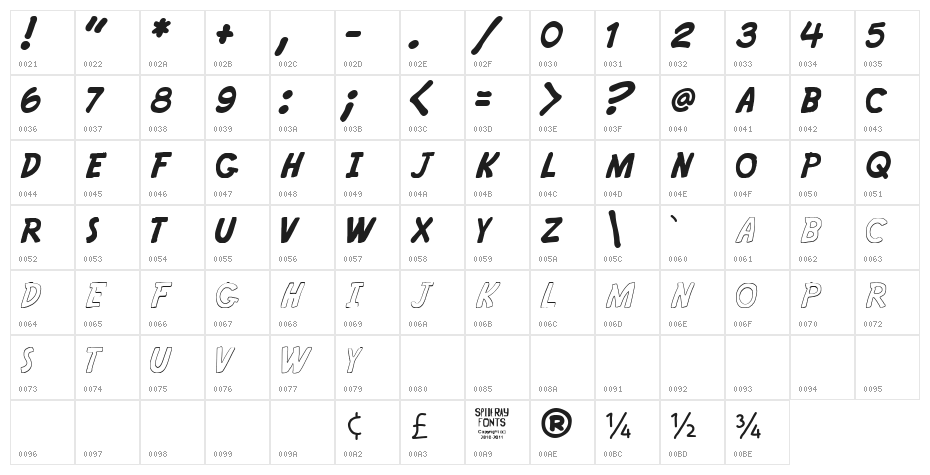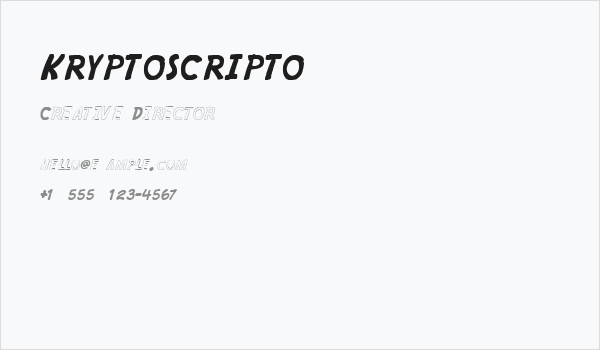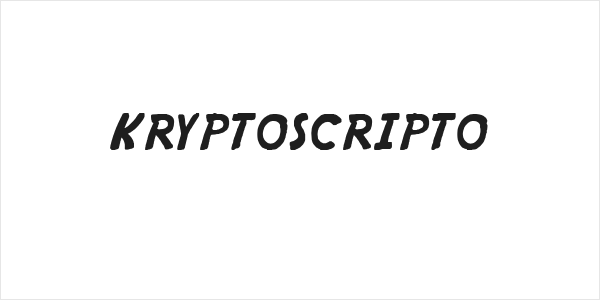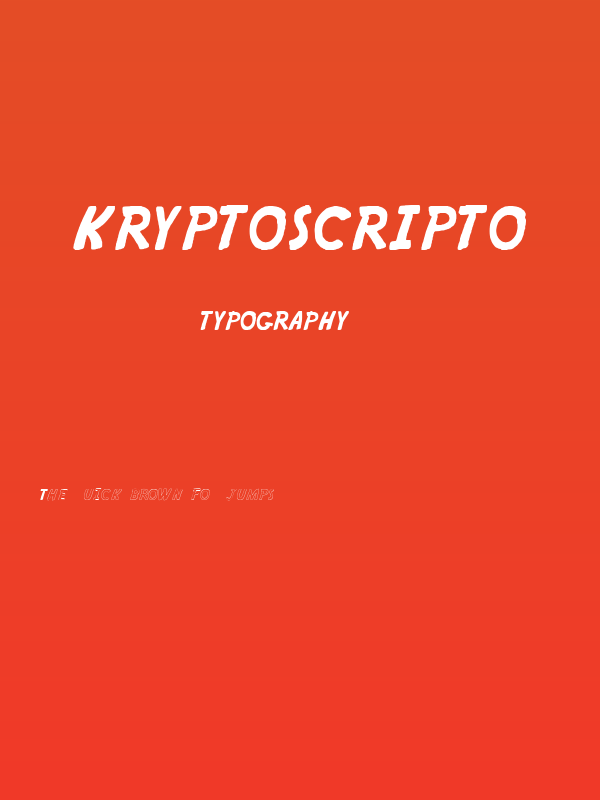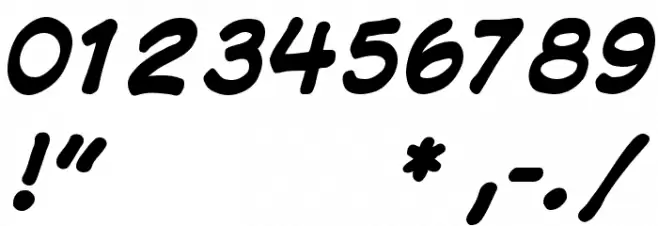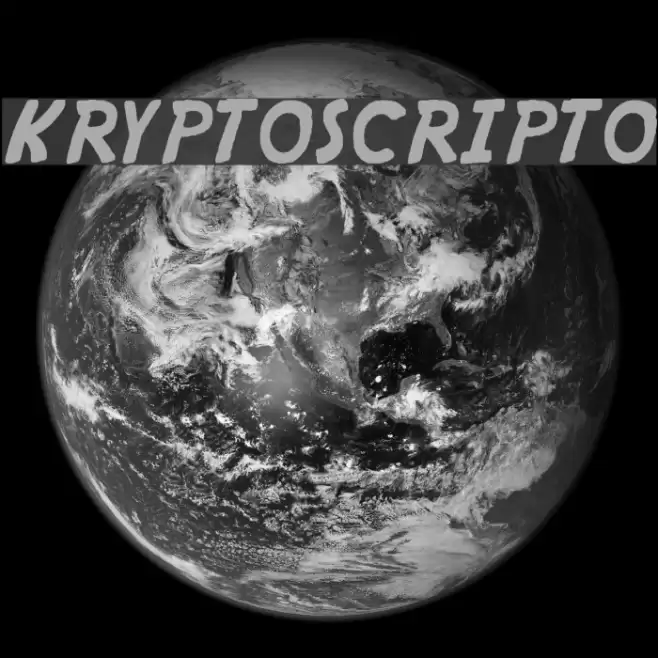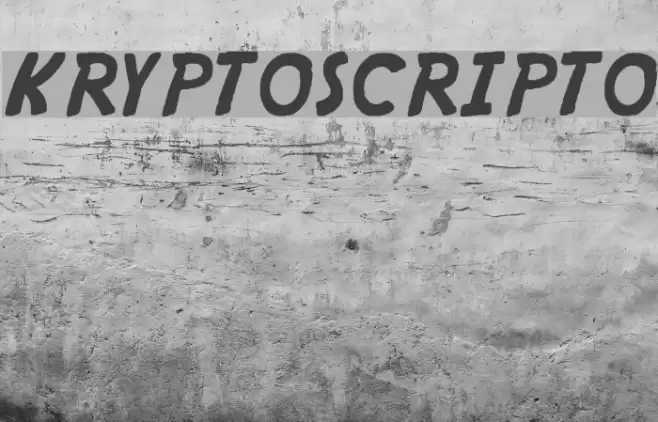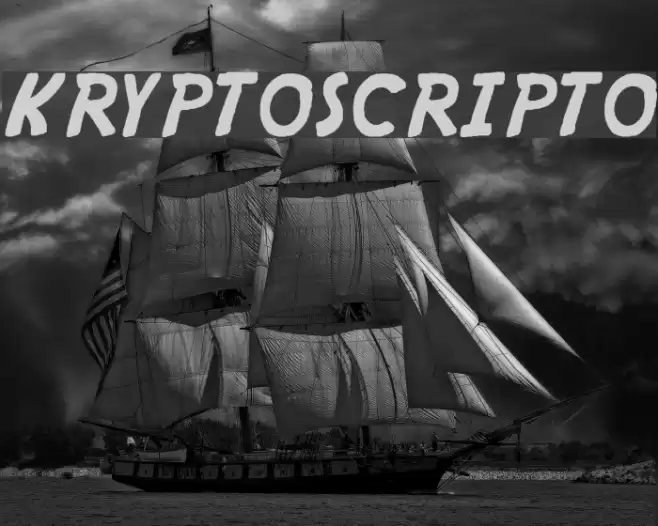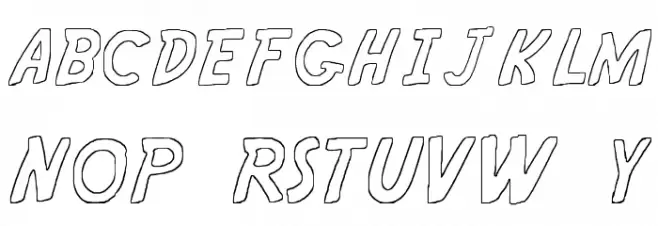
KRYPTOSCRIPTO Font
✎ TV show
| Projets proposés | Ideal for projects that require a bold statement, such as posters, logos, and branding materials. It can also be used for headlines and titles that need to capture attention. |